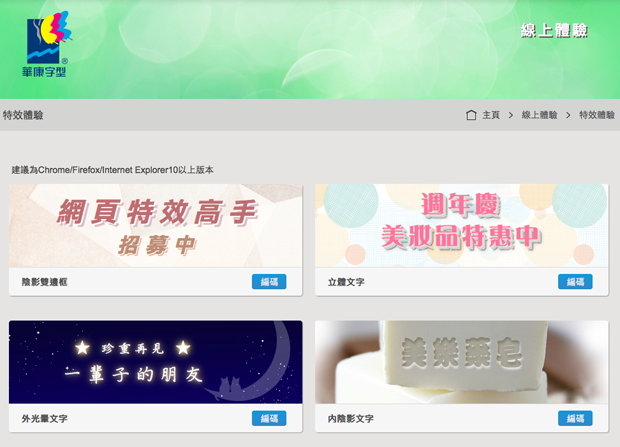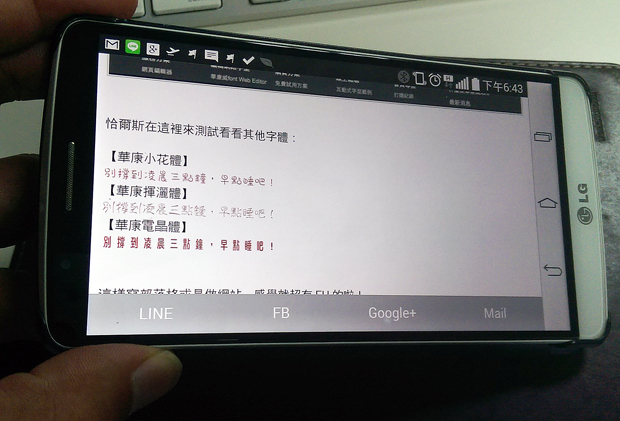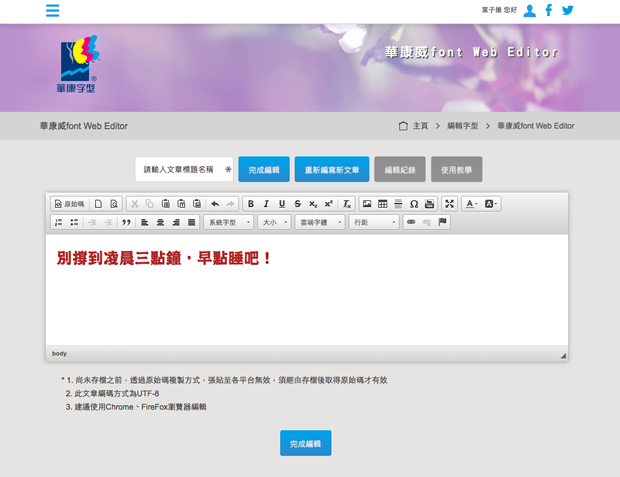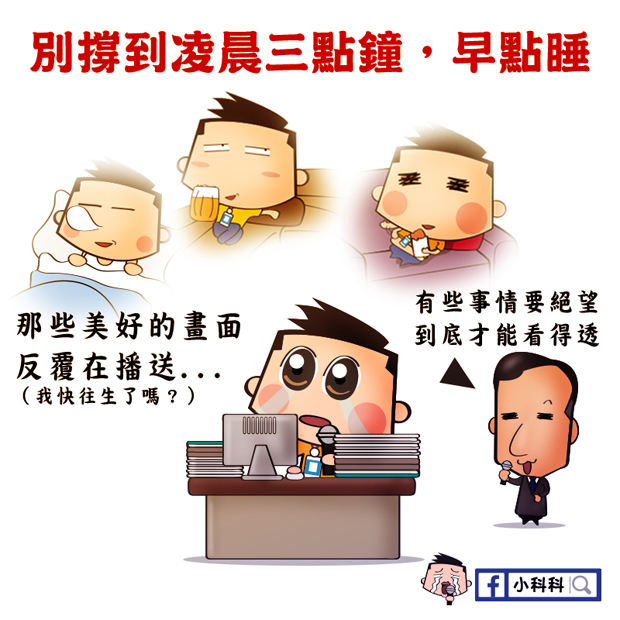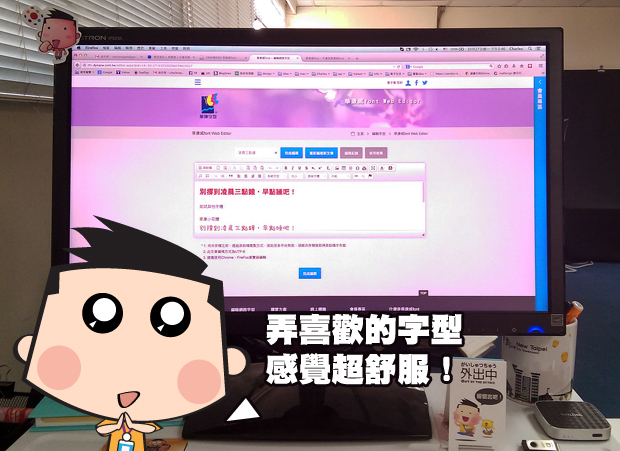
【秘技】網路字型革命!華康威font讓網站和部落格耳目一新!
老早就想要在部落格用華康字型了,今天要介紹的是「華康威font」網頁字型,雲端字體真的可能是未來字型設計上的新趨勢呢!
公司的網頁有救了… 我們家字型真的設計得很慘
我覺得不論是網頁設計師、App 開發、部落客…都滿適合使用華康威font的,這就從部落客的角度來切入,帶大家體驗一下吧!
大家都看得到的個人化字體
一般的網頁設計師或是像恰爾斯平常有在畫圖的人,應該都有使用過華康字型,目的就是希望和別人的設計不一樣,或是加強圖裡面文字的張力,無論是標題、對話方塊或是內文,怎麼使用都比一成不變的「新細明體」、「標楷體」、「微軟正黑體」要好,顯得更自由、更奔放。
字體漂亮、有效果,很容易就可以很吸引人囉!使用華康威font就能一次擁有 191 套華康字型,網頁整個可以用到不行,重點針對瀏覽器,有支援 Chrome、Safari、IE、Firefox、Opera 瀏覽器,大家電腦就算沒有安裝華康字型,也能完美顯示你網站上設定好的字型,輕輕鬆鬆就可以做好一個很有設計感、有 Sense 的網站。
你的網站大家找得到嗎?
當然如果為了美觀,如果你網站裡面都是「用圖片」來呈現這類字體效果的話,在 SEO(搜尋引擎最佳化 – Search Engine Optimization)方面就會很慘,Google 在你的網站裡面找不到這些關鍵「文字」字串,導致影響整個網站的瀏覽表現。
像以前畫這張圖的大標,在 Google 上可能找不到。
(畢竟是圖,不是文字)
這張漫畫就是使用「華康榜書體」的字型當標題,一般我們想要在部落格或網頁上給網友呈現這樣的字體幾乎是不可能,除非將這串字轉換成圖片,再貼到文章裡面,既麻煩又沒有彈性。這個時候「華康威font」就要來解救我們了。
你在網頁上也可以打出很特別的字唷!
特殊效果小恰都示範在部落格,可以自己玩看看
這樣 Google 在你的文章中就找得到這樣的關鍵字了。
只是可能你系統裡有安裝這些字型,但是別人的電腦沒有安裝,所以原本我們設計的美美字型就沒辦法呈現出來。
這裡來告訴大家怎麼做的吧!
趕快告訴我!不然扣你薪水…  要說了啦!
其實華康威font Web Editor 的編輯介面就像你在寫部落格的後台一樣,真的是非常簡單!要置中、底線、插圖片、貼 YouTube…都沒有問題,編輯器方面就是 WYSIWYG(所見即所得的效果),我們甚至可以把部落格正在編輯的文章直接貼進來,再進行字體的選擇編修。
編輯完成後,就會幫我們輸出網頁的 html 原始碼,複製這些 code 之後,只要回到你自己的部落格後台或是網頁的編輯器進行原始碼的貼上就可以了,操作上真的非常直覺,簡單到一個不行!
這樣寫部落格或是做網站,感覺就超有 FU 的啦!
另外在網頁上的圖片加上文字特效也沒有問題,就是搭配 CSS 特效和文字效果的設計,可以做一些內陰影或其他特效,有興趣的朋友可以自己玩玩看唷!
特殊效果小恰都示範在部落格,可以自己玩看看
當然漫畫加上文字也沒有問題,不用進 Photoshop 上文字。有的時候我們看一些網站或是 App,在自己的筆電上看都正常,但在手機或平板上看就會出包,像是字體出現破損或是霧霧的,甚至是跟原來看的效果差很多,這些都會影響到我們閱讀的感覺。
基本上我們透過網頁、手機、行動裝置、平板電腦來看剛剛講的這些雲端網頁字體,真的都不會有問題,這類裝置都可以完整顯示華康威font 的字體,不用擔心大家在不同裝置會有不同效果。
特殊效果小恰都示範在部落格,可以自己玩看看
心得:
恰爾斯覺得這樣的服務對於網頁或 App 的設計師來說真的是一大福音,經營部落格的朋友也有新的呈現方式。使用華康威font 這樣的網路字型服務,不用安裝什麼額外的字體檔案,就能完美在各類平台上呈現這些很有特色的字體,有夠好玩的,趕快來試試看啦!推薦給大家囉!